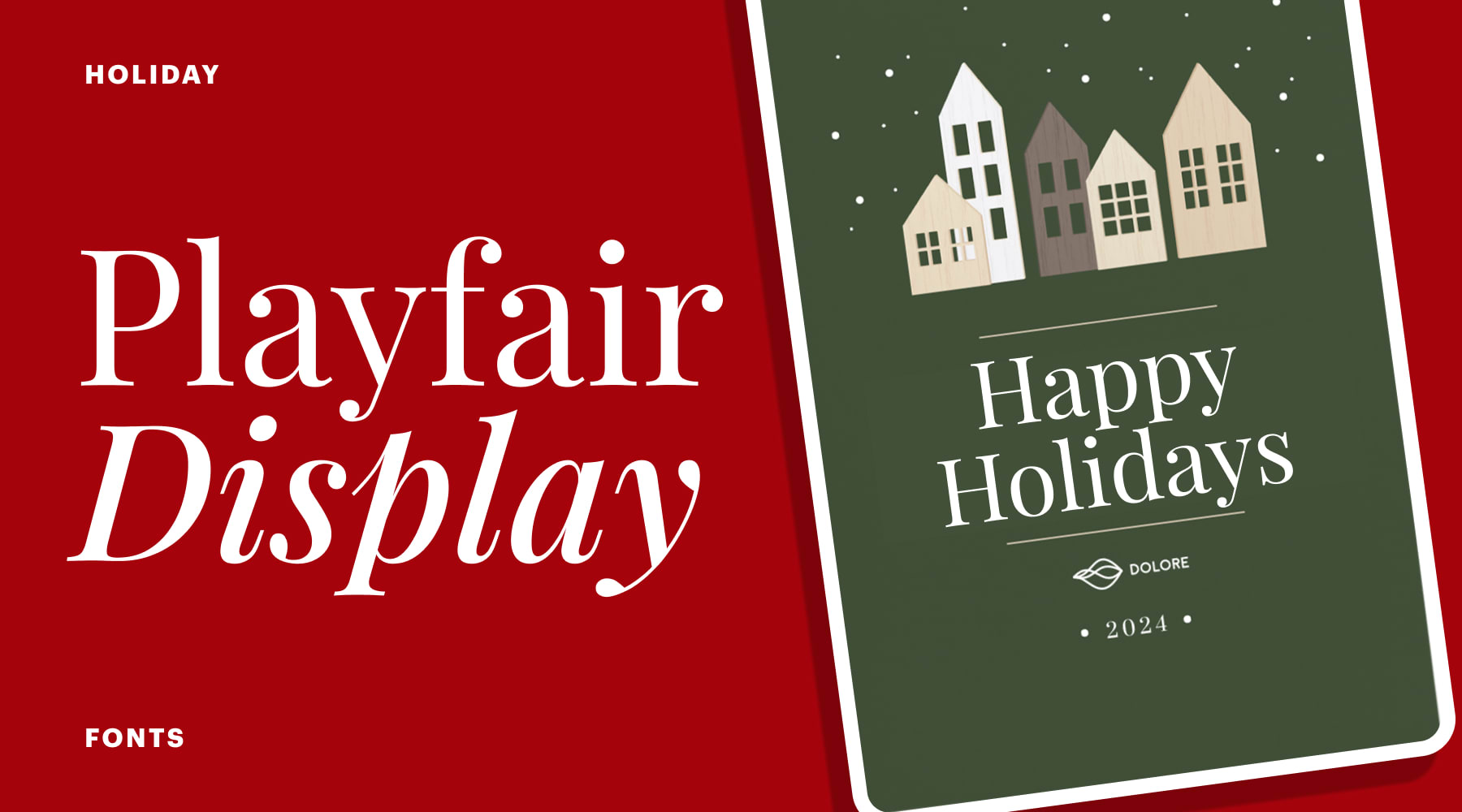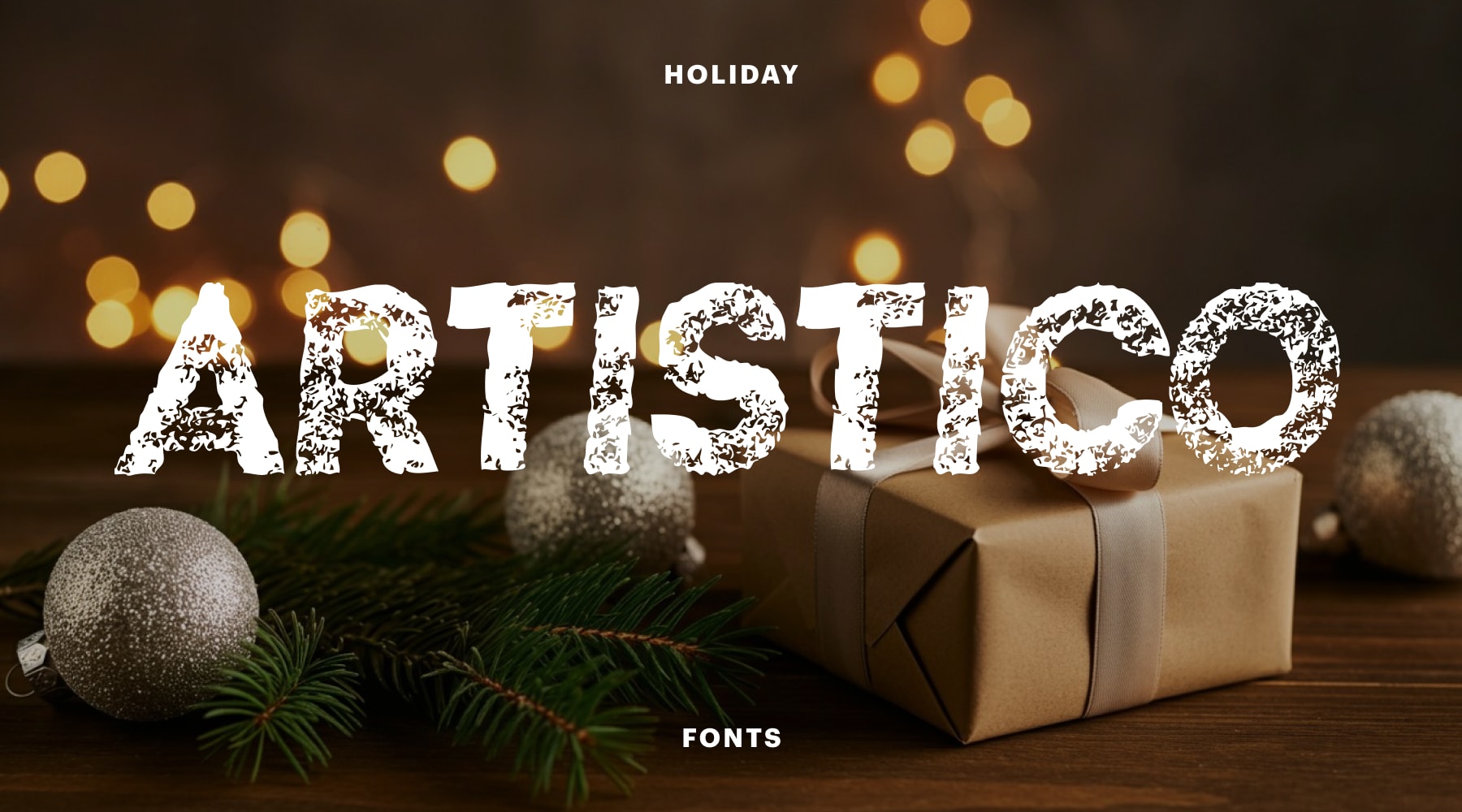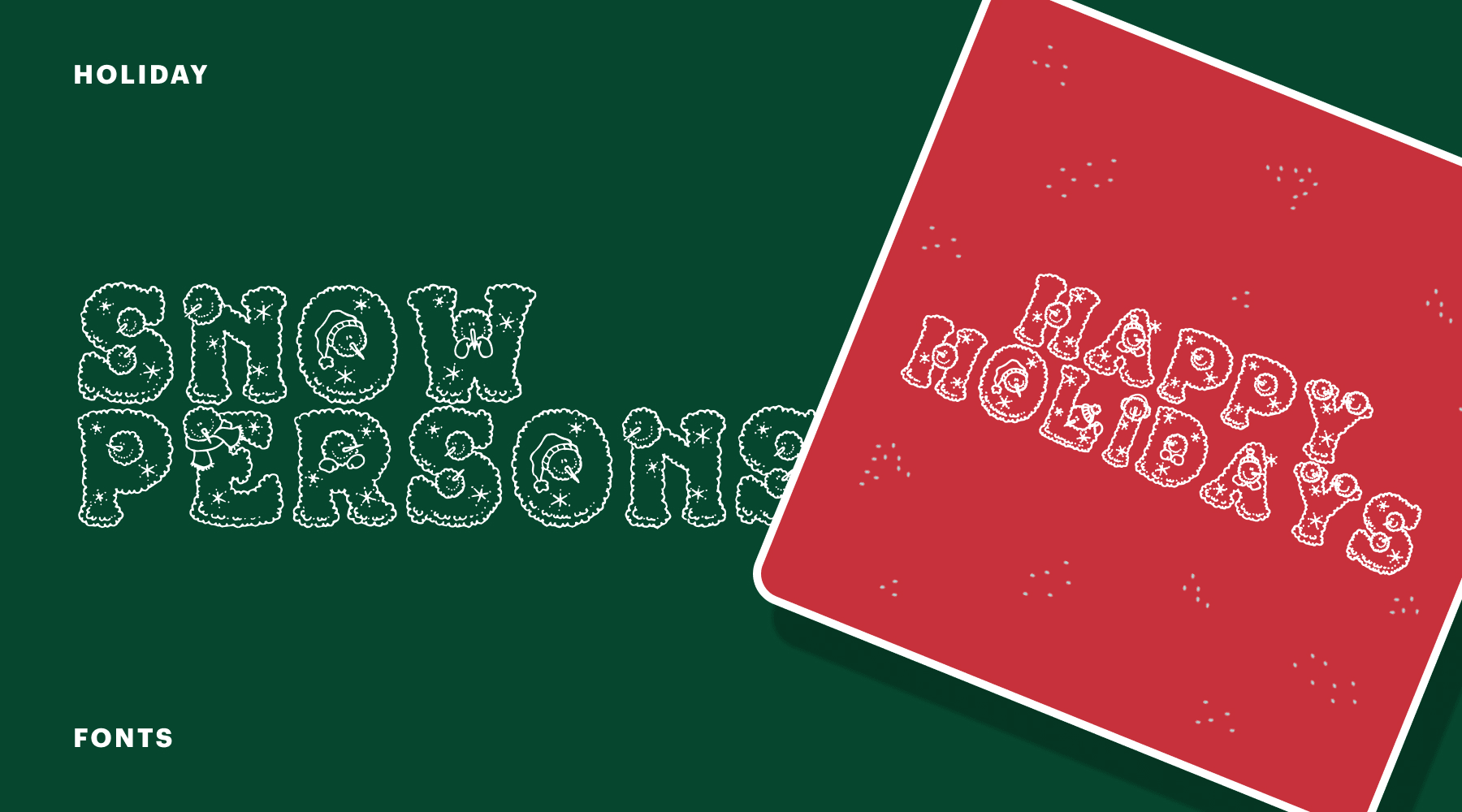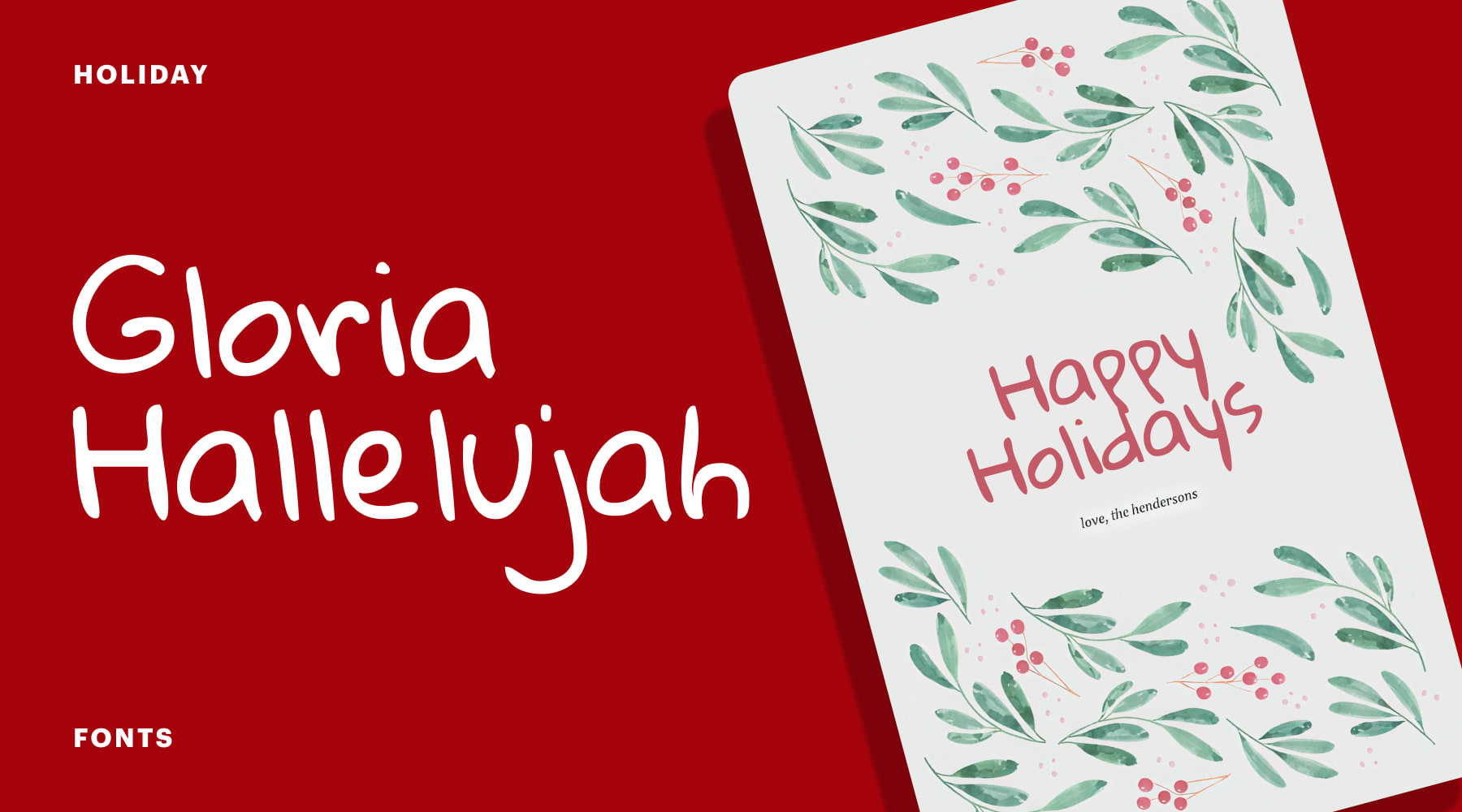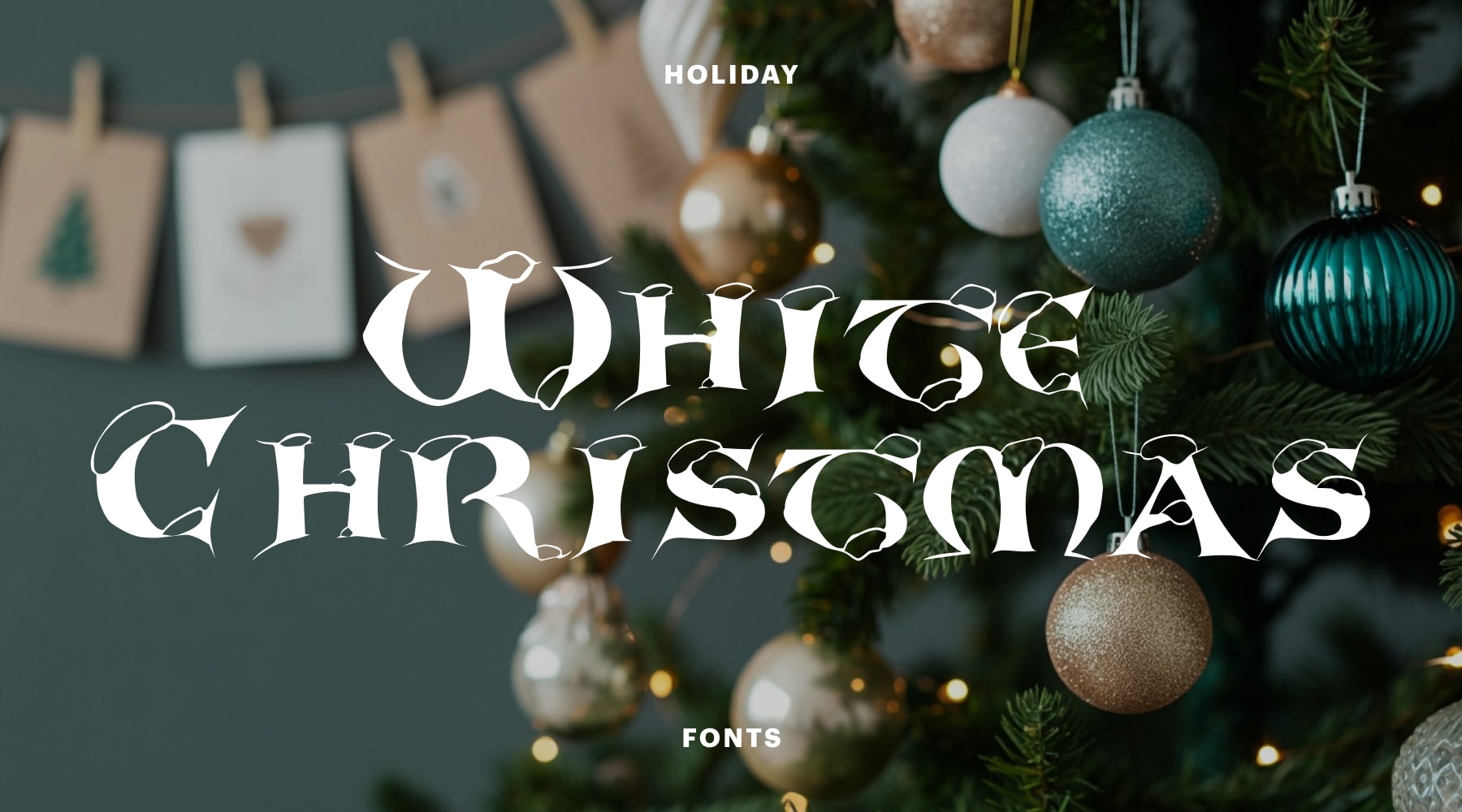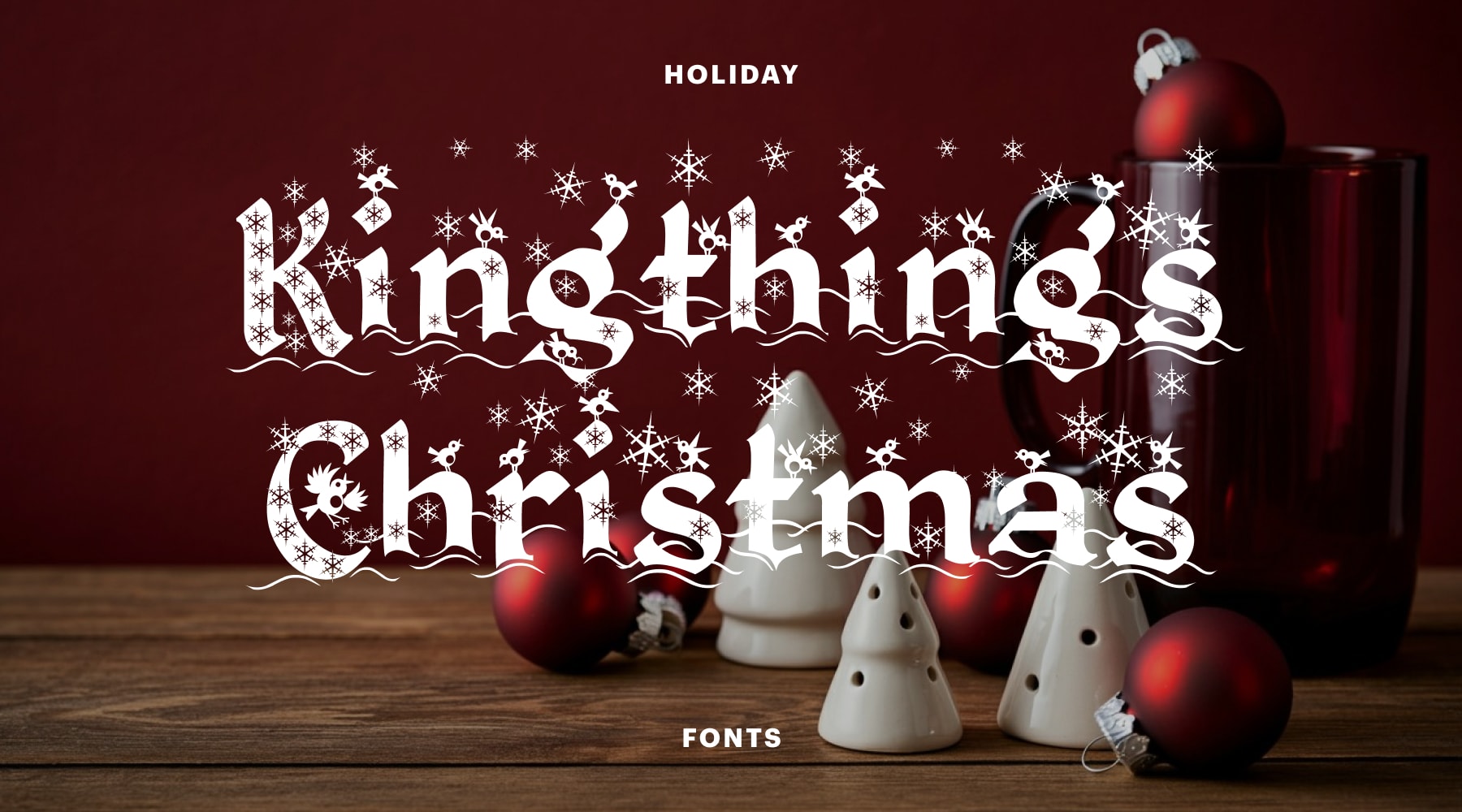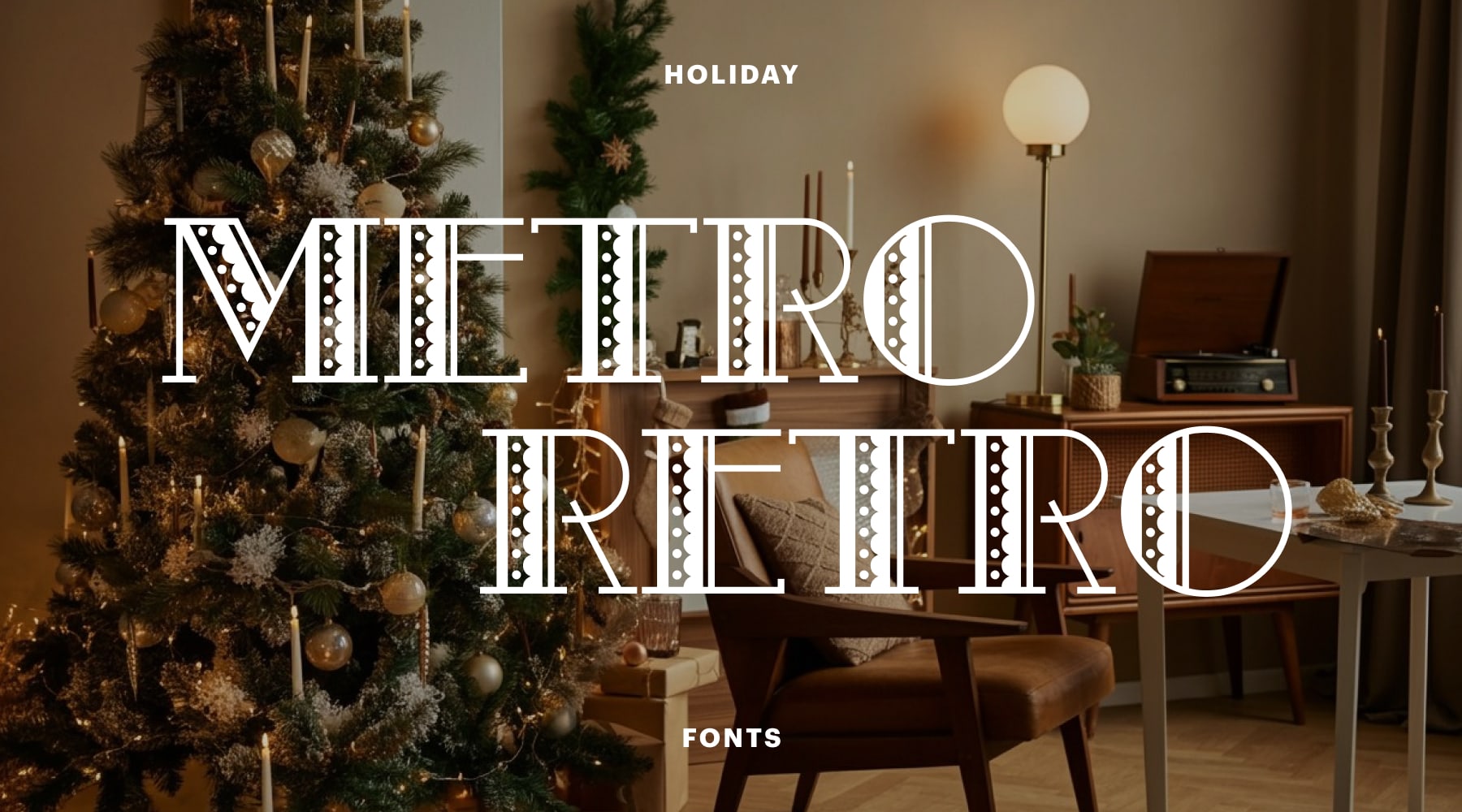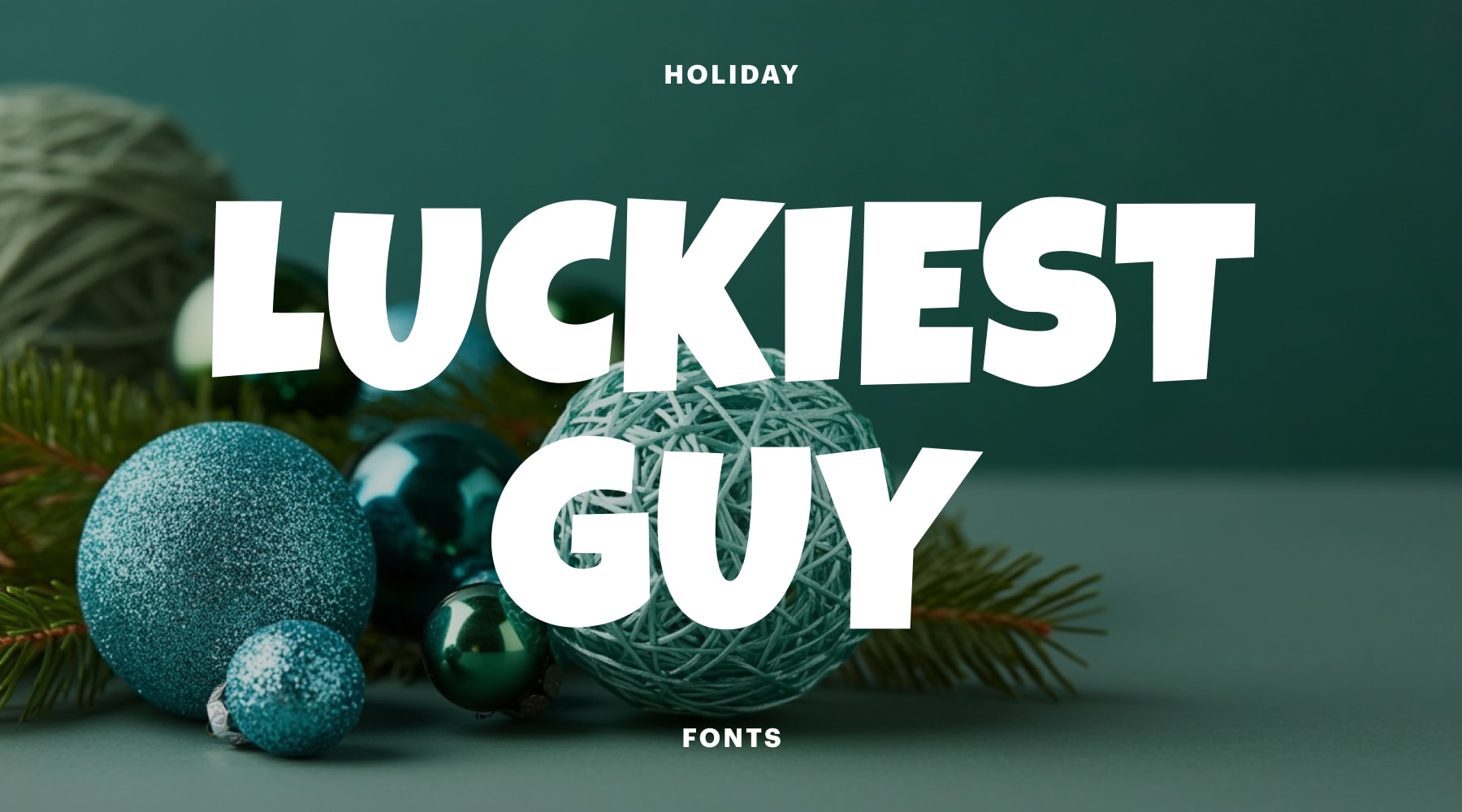
Nun ist es nicht mehr lang bis zur (Vor-)Weihnachtszeit! Als kleines Geschenk von uns finden Sie hier 31 kostenlose Schriftarten, die Sie für Ihre weihnachtlichen Unternehmensneuigkeiten, Social-Media-Posts, Flyer, Verpackungen und Weihnachtskarten verwenden können.
Die Auswahl reicht dabei von ganz klassischen festlichen Schriften mit geschwungenen Linien und schneebedeckten Buchstaben bis hin zu eher schlichten und modernen Varianten.
Ob Ankündigung für Festtagsdeals oder Weihnachtsgrüße, die Wahl einer passenden Schriftart für die Feiertage verleiht Ihren saisonalen Kampagnen mehr Persönlichkeit. Dabei sollten Sie die bewährten Regeln zur Auswahl einer Schriftart beachten: Alle wichtigen Informationen müssen deutlich erkennbar und gut lesbar sein und die einzelnen Schriftarten auf der Seite sollten sich gegenseitig ergänzen.
Vertrauen Sie auf Ihren kreativen Instinkt, beachten Sie Ihre Markenrichtlinien, sofern vorhanden, und nehmen Sie sich genügend Zeit, um verschiedene Varianten auszuprobieren und zu beurteilen. Die nachfolgenden weihnachtlichen Schriftarten sind Stand September 2025 für den kommerziellen Gebrauch kostenlos.
- Weihnachtsgrüße und Werbebotschaften in der Adventszeit können Ihre Sichtbarkeit erhöhen und die Verwendung einer Weihnachtsschriftart ist dabei fast so wichtig wie die Botschaft selbst.
- Schriftvertriebe im Internet bieten kostenlose Weihnachtsschriften zum Download an. In diesem Artikel finden Sie Links für die besten handschriftlichen, serifenbetonten, serifenlosen, verspielten, Retro- und Vintage-Schriften.
- Jede dieser Schriftarten eignet sich für unterschiedliche Designs, von heiter bis traditionell. Wählen Sie am besten eine Schrift, die zu Ihrem Branding und Ihrer Marketingstrategie passt.
1. Schreibschrift
Die geschwungenen Linien dieser Schriftarten ahmen handgeschriebene Buchstaben nach – sie eignen sich also ideal für elegante Weihnachtskarten, festliche Speisekarten und als werbewirksame Postkartenschriften. Schreibschriftarten eignen sich besonders für opulente Überschriften, aber weniger für den Text selbst, da sie in kleineren Schriftgrößen schnell unlesbar werden.
1. ChopinScript
Eine elegante und formelle Schriftart mit einer Prise freundlicher Verspieltheit: ChopinScript macht auf Einladungen für vorweihnachtliche Veranstaltungen und auf Weihnachtskarten eine gute Figur. Im Vergleich zu manch anderen Schreibschriftarten ist sie einfach lesbar.
2. Ochre Script
Die geschwungene, romantische Kalligrafieschrift verleiht Weihnachtseinladungen, Social-Media-Posts und Weihnachtskarten für Unternehmen handgeschriebenen Charme.
3. Fresh Orange
Fresh Orange wirkt dank ihrer variablen Strichstärken flott und lebendig – eine tolle Wahl, wenn es eine Handschrift sein soll, die nicht altmodisch wirkt. Der Buchstabenfluss fühlt sich energetisch an und verleiht dem Text frische Eleganz.
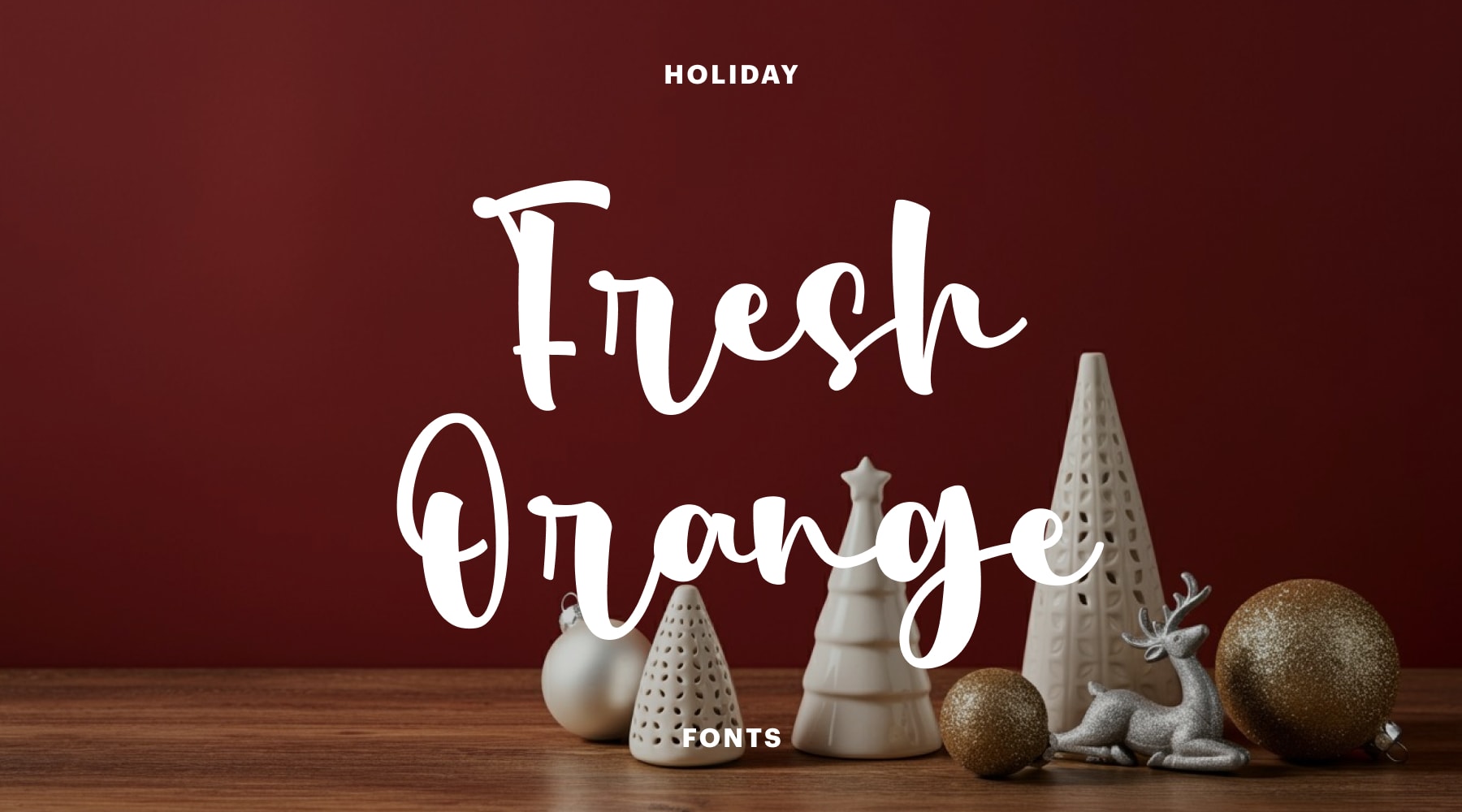
4. Good Vibes
Als verspielte und funky Schriftart mit Flair der 60er- und 70er-Jahre stellt Good Vibes sicher, dass Ihre Beiträge in den sozialen Medien ins Auge fallen und Ihr saisonales Produktmarketing einen entspannten, coolen Touch erhält.
5. Noelan
Diese Handlettering-Schrift mit zauberhaften Schnörkeln bringt festliche Verspieltheit in Ihr Marketing, von Werbetechnik bis zu Social-Media-Posts.
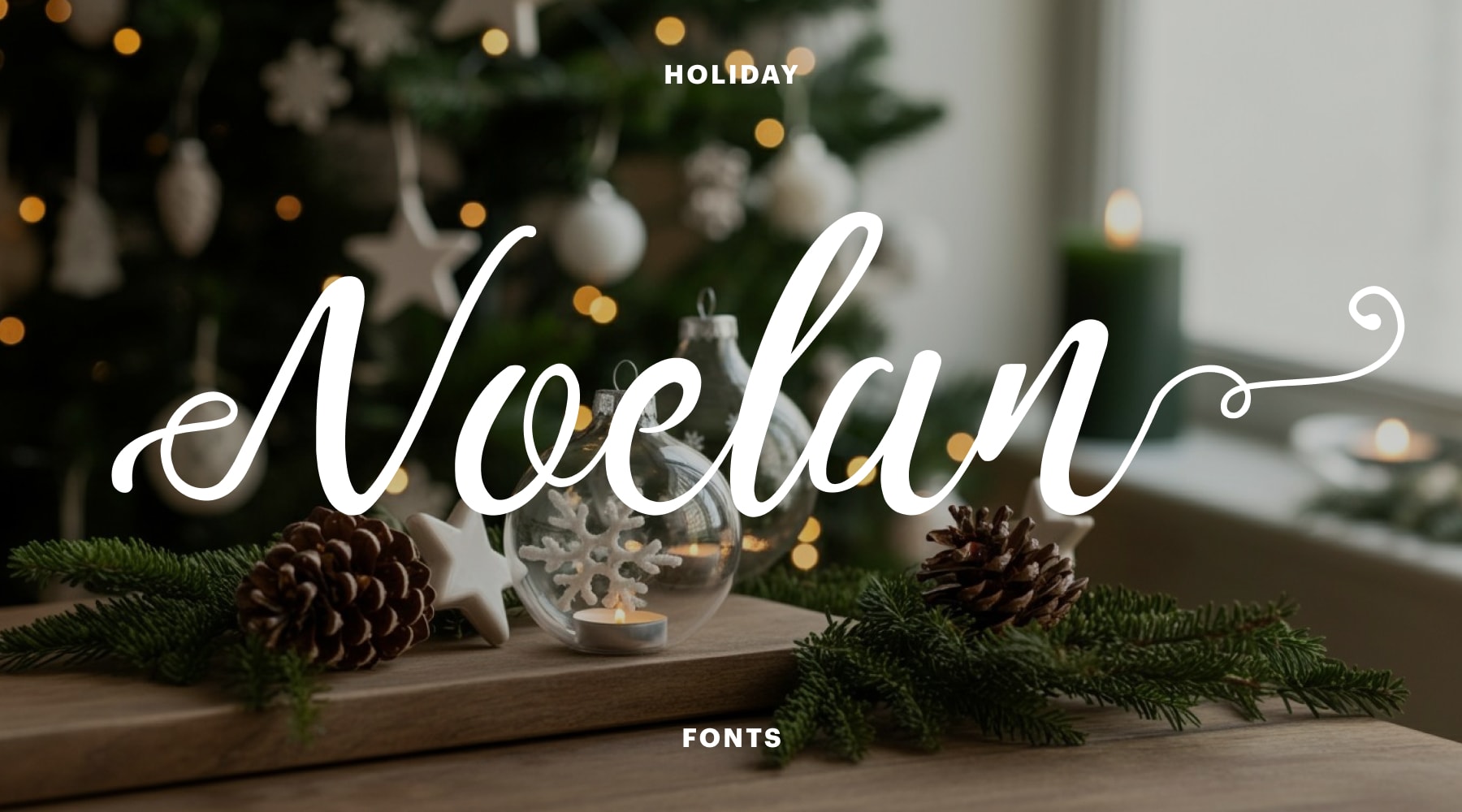
6. League Script
Die filigranen Linien von League Script wirken wohlüberlegt, ästhetisch und etwas kokett.
Wählen Sie diese Schrift, wenn Sie Ihrer gedruckten oder digitalen Kommunikation einen Hauch von Vertrautheit und Glaubhaftigkeit verleihen möchten.
7. Abys
Mit ihren unregelmäßigen, etwas rauen Pinselstrichen ist die Handschrift Abys perfekt für alle, die sich weihnachtliches Branding mit Charakter wünschen und ihren Überschriften oder Social-Media-Posts einen Schuss Moderne und Aufregung verleihen möchten.
2. Serifenschriften
Serifenbetonte Schriften wirken dank der kleinen Häkchen am Ende eines jeden Federstrichs oft von Haus aus traditionell. Sie machen sich großartig für Drucktexte sowie für Weihnachtsverpackungen, Werbetechnik und Branding mit gehobenem Look and Feel.